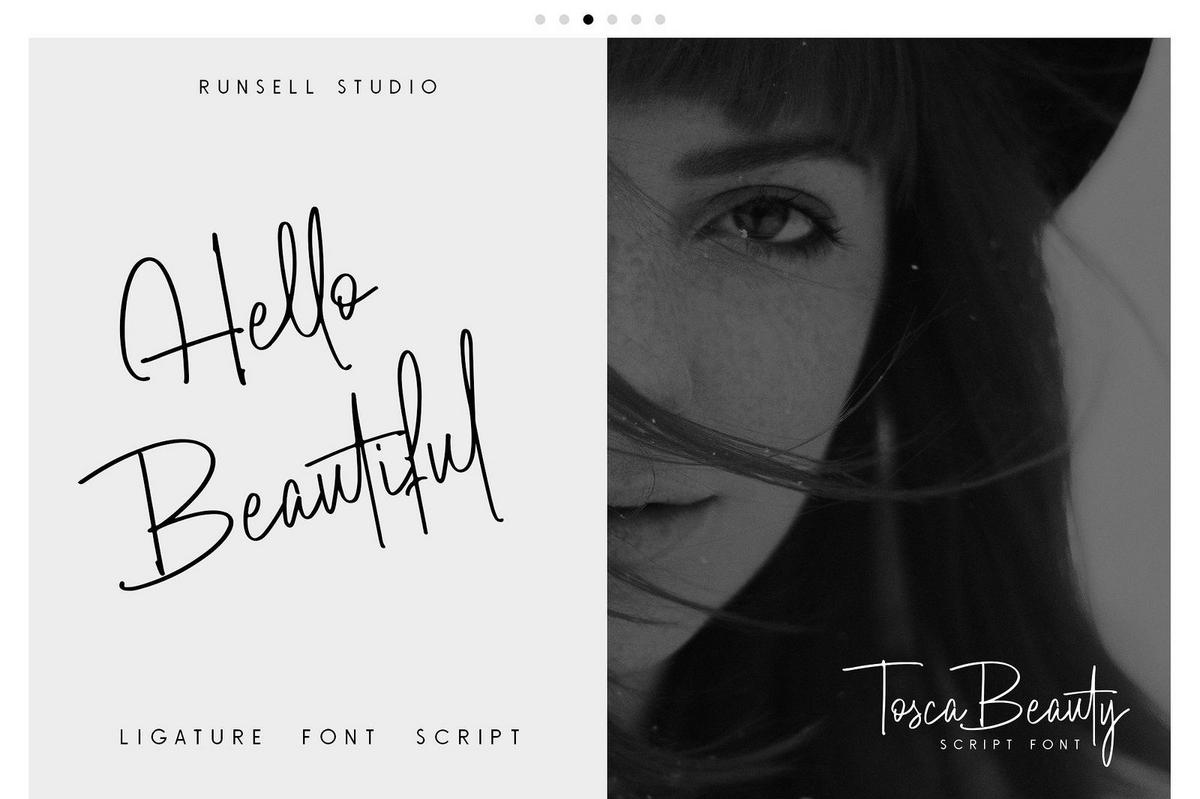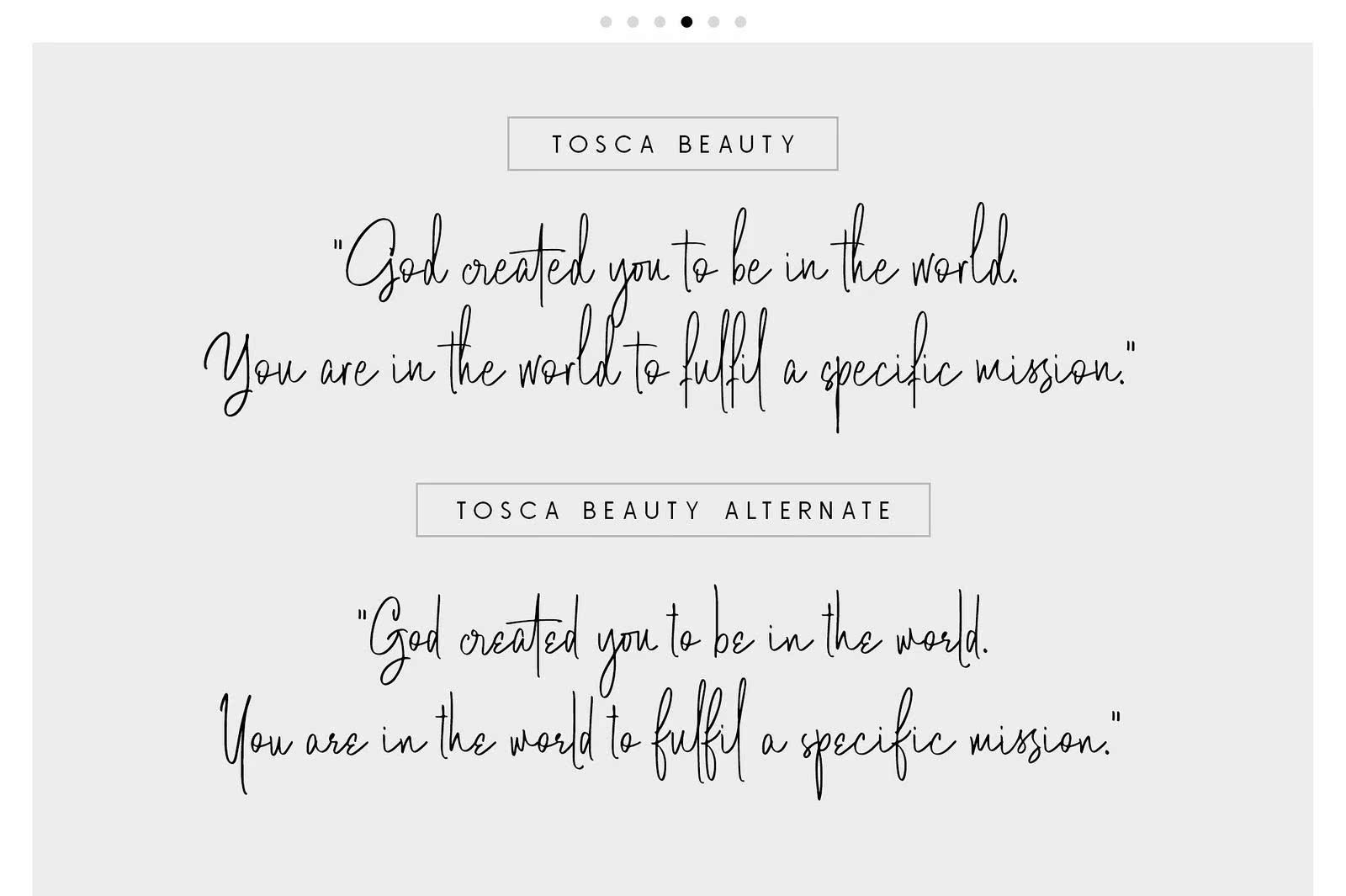
RunSellStudioIntroductionGNEWScriptFont to Cabeauty。优雅的特性可以使您的设计看起来像是经过验证和手工制作的。此字体适用于您的签名、标识、婚礼宣传、报价、网站标题、包装、品牌、名片、,Fashion Magazinea and More.ToscaBeauty可用于其他字体和连字。RunSell Studio介绍将手写字体命名为Cabeauty。优雅的特性可以使您的设计看起来真实可信,并且是手工制作的。此字体适用于您的签名、标识、婚礼宣传、报价、网站标题、包装、品牌、名片、,时尚杂志Azionine and More.Toscabeauty可用于替代方和韧带。